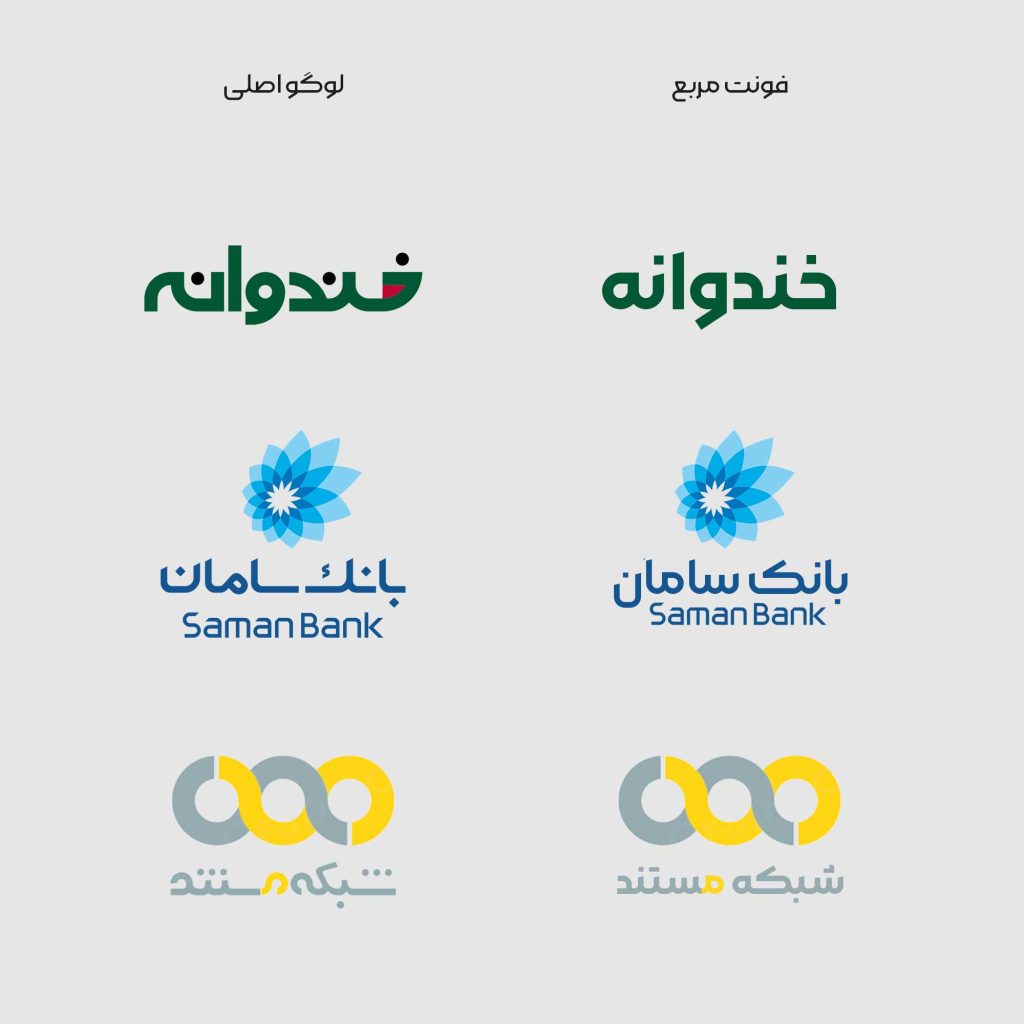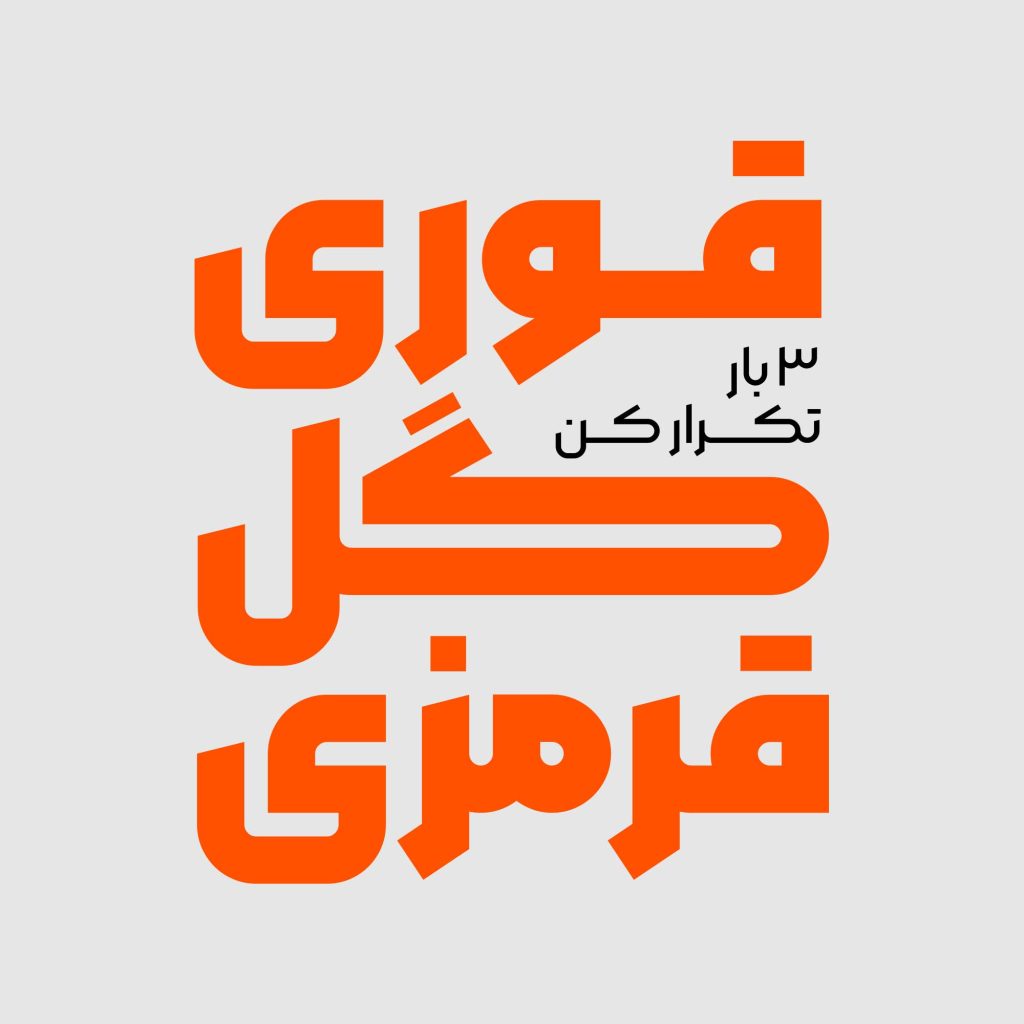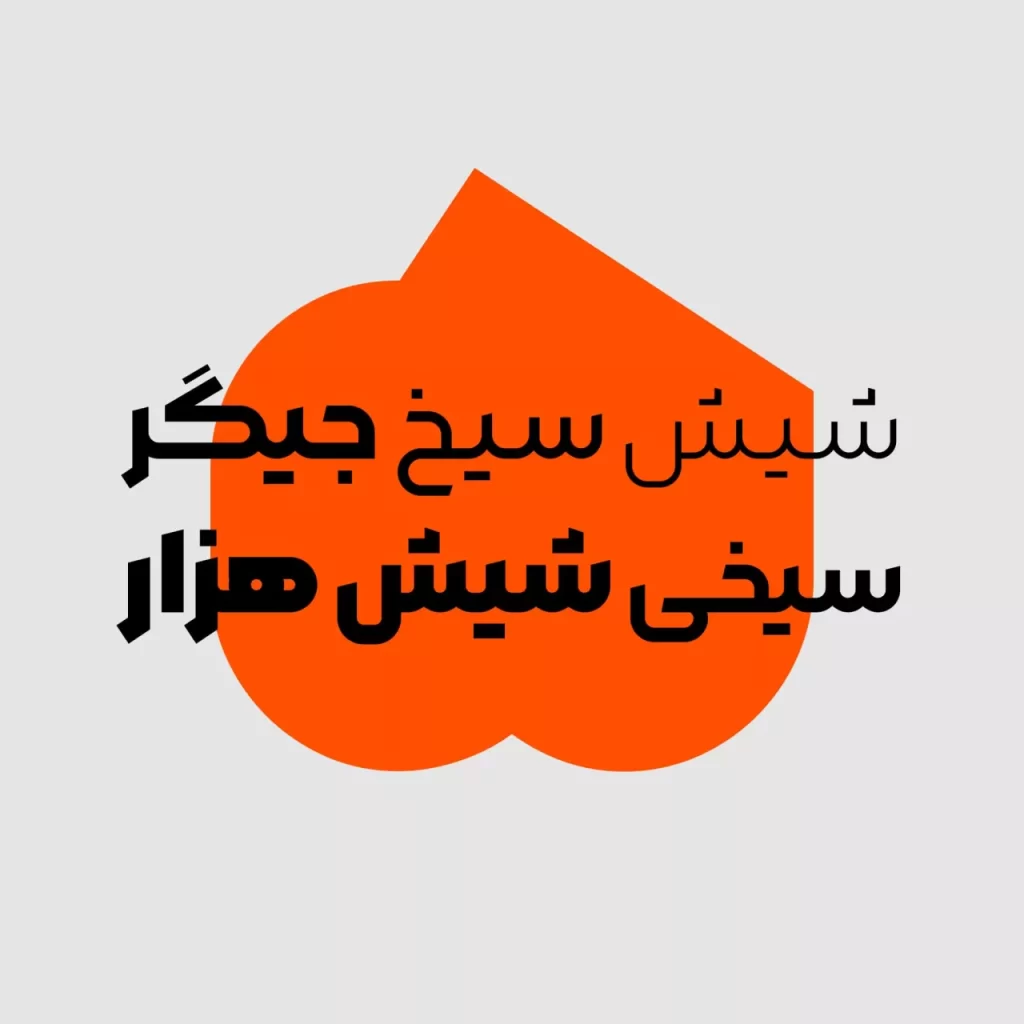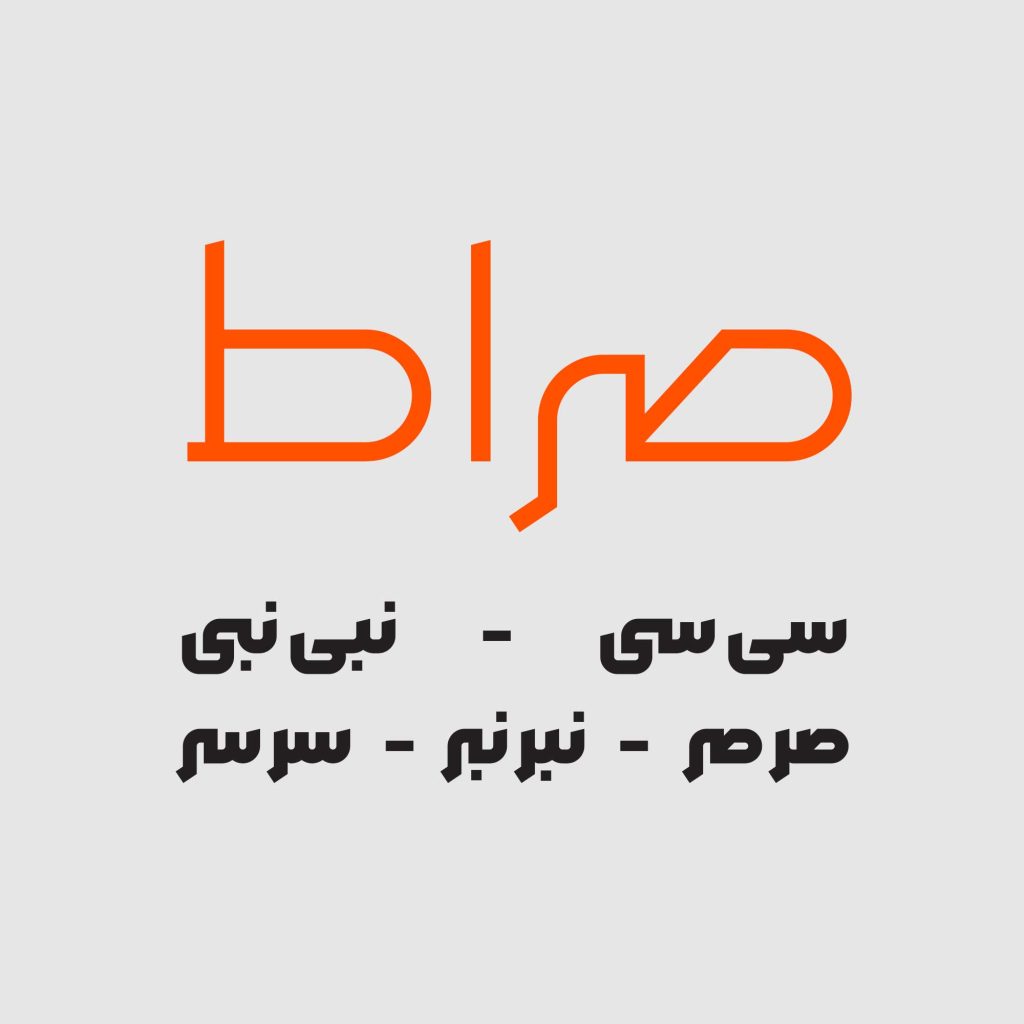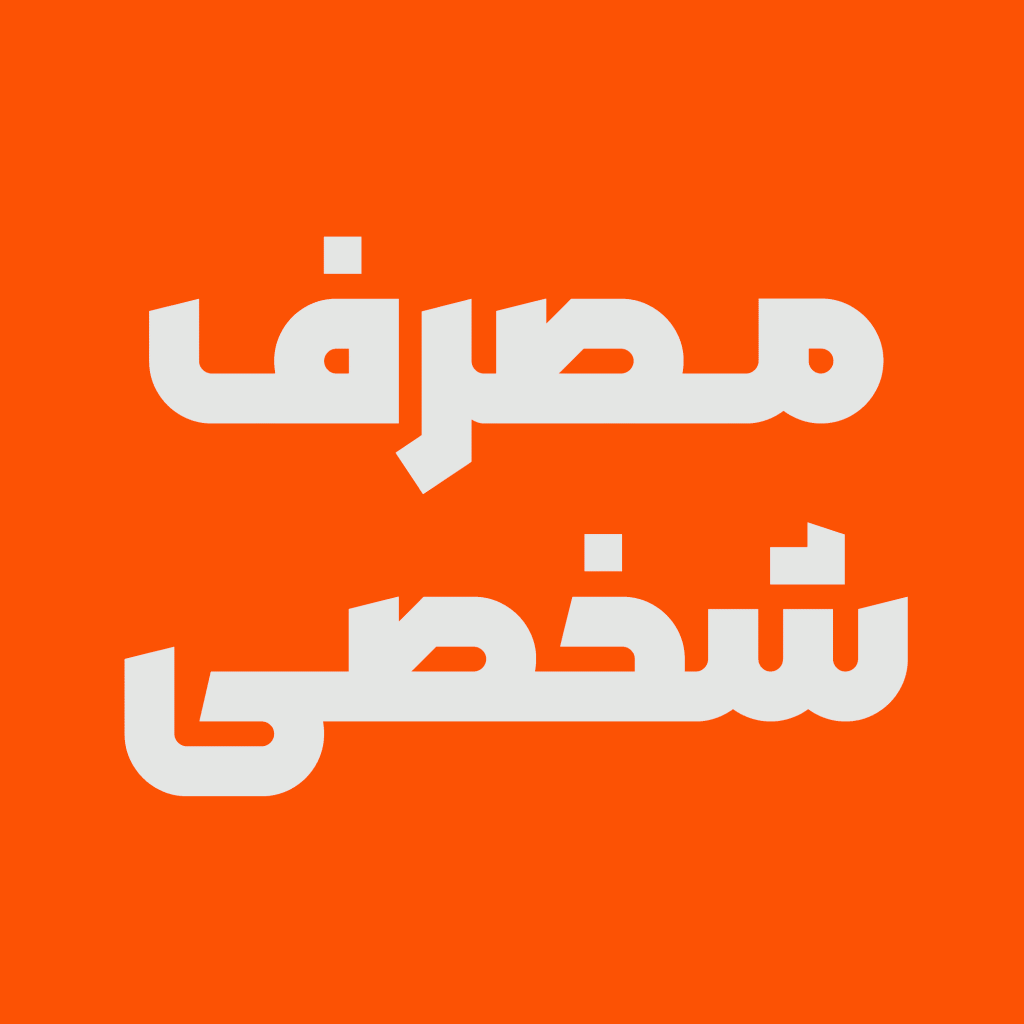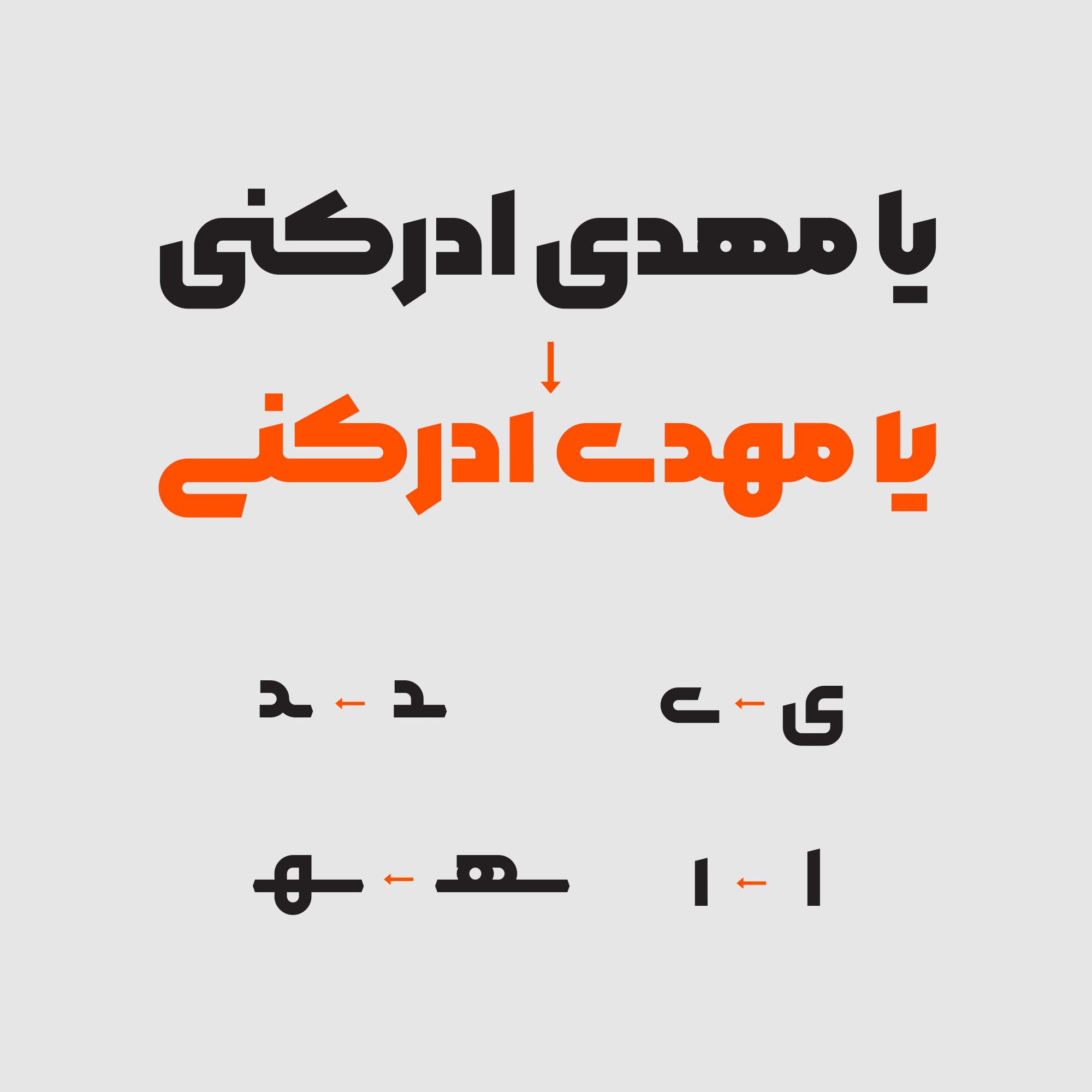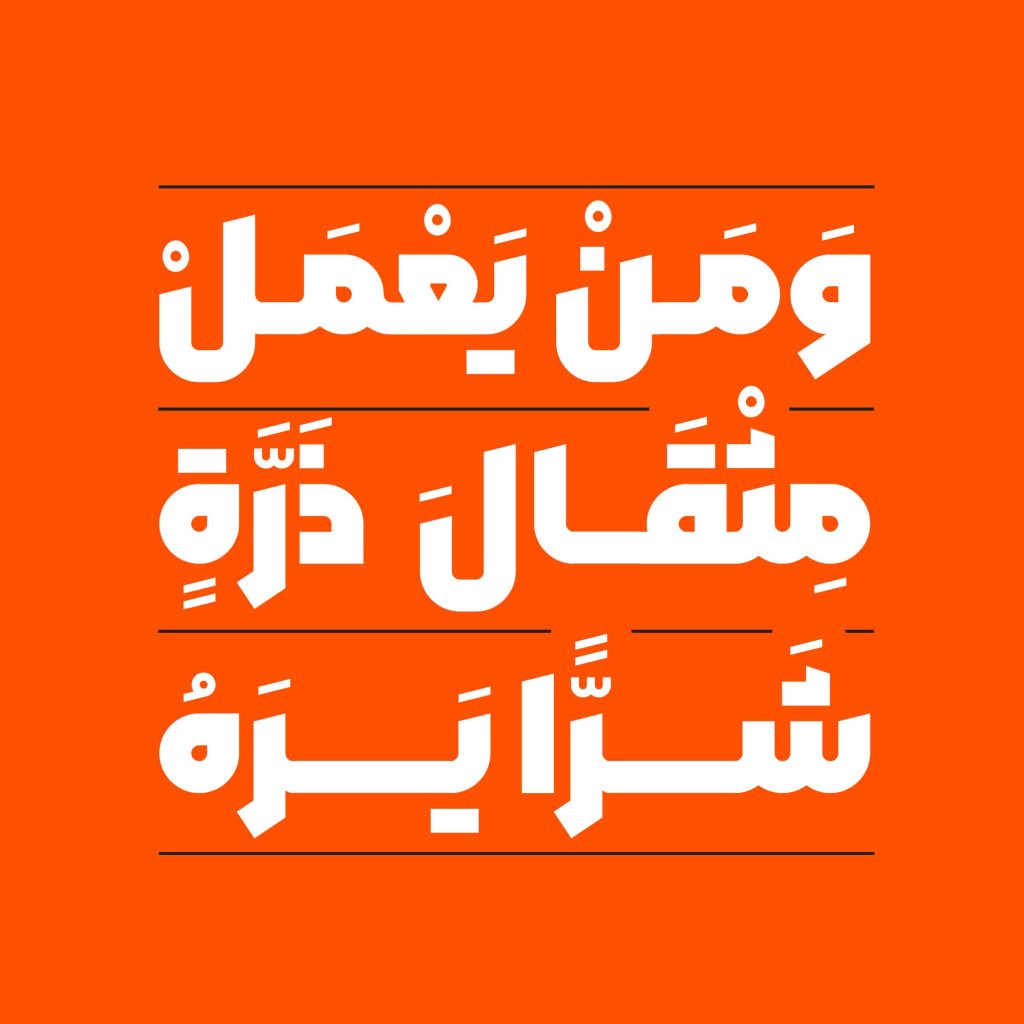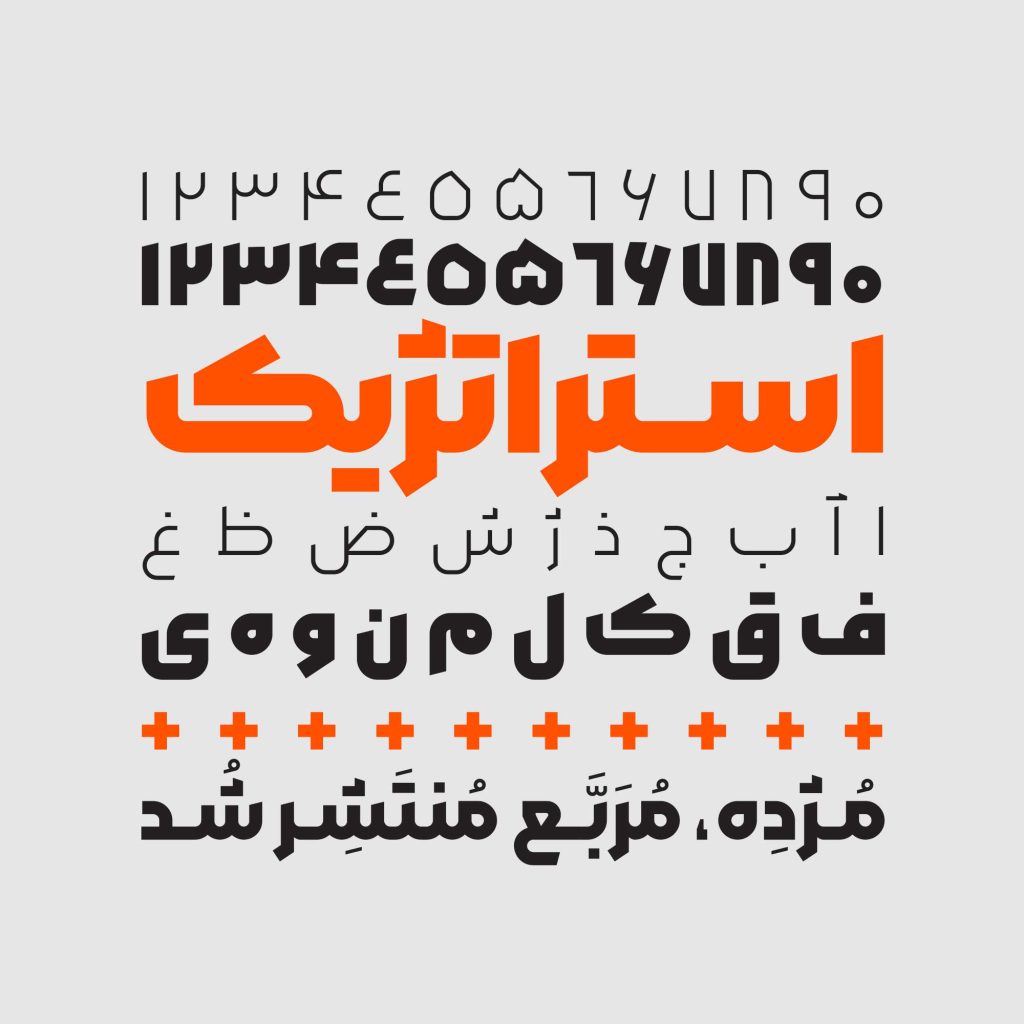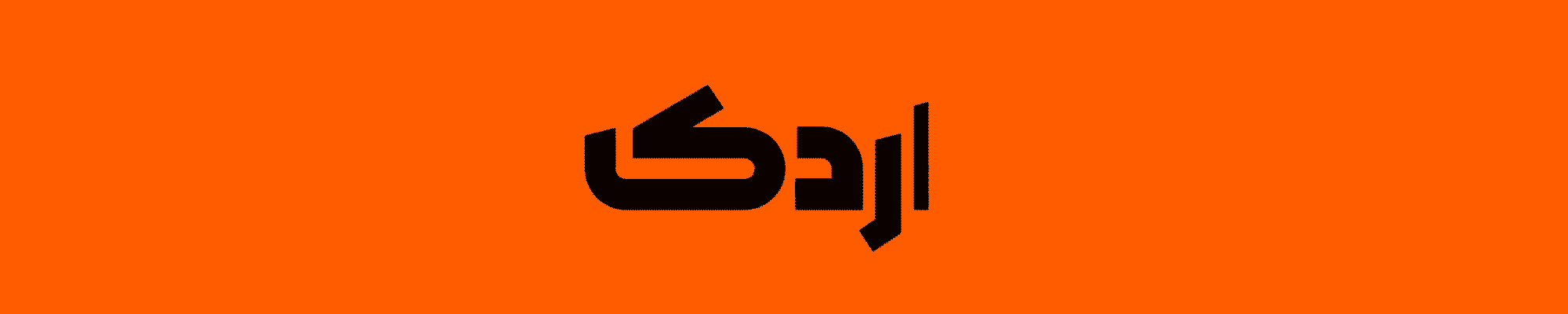
فونت مربع
فونت مربع تایپ فیسی که با دانلود و خرید آن تقریبا اکثر نیاز های خود را مرتفع می سازید. اساس و شاکله این قلم مبتنی بر خانواده کاملا هندسی است . از هم نشینی شبکه ای از دایره ها و مربع ها این قلم جذاب و مدرن تشکیل گردیده است. تایپ فیسی برای کلمات و عبارات کوتاه که جاذبه و گیرایی آن بی شک نگاه خوانندگان را به خود جذب می نماید.
این قلم با روحیه پر انرژی و امروزی که دارد مناسب برای موضوعات تجاری و مدرن و تبلیغاتی است از قبیل طراحی وردمارک، اسلاید و کاورهای تبلیغاتی ، مطبوعات شبکه های اجتماعی و چاپ و بسته بندی و … همانطور که پیش تر نیز خدمت شما عرض کردیم مربع قلمی همه منظوره است.
با دقت در فرم های طراحی گلیف های این تایپ فیس، می توان دریافت که نسبت فضای مثبت به فضای منفی در نظر گرفته شده و کِرو ها دقیقا با محیط دایره همراستا گشته اند.
از نقطه نظر شباهت می توان این قلم زیبا را می توان هم نوع و هم شکل فونت رخ در نظر گرفت. هر دو این تایپ فیس ها از خانواده هندسی می باشند . همانطور که واضح و مشخص می باشد توجه به جزئیات در هر دو این قلم ها امری غیر قابل انکار می باشد.
مربع مناسب پوستر عناوین و ساخت لوگو تایپ
فرم طراحی در این تایپ فیس مناسب برای استفاده و طراحی ورد مارک Wordmark می باشد یعنی می توان از این قلم به عنوان لوگو تایپ نیز با عنایت به هندسی بودن و فرم خاص آن نیز استفاده نمود . پس می توانید به کمک نرم افزار های طراحی از جمله آدوبی ایلسترتور و فتوشاپ یا حتی اینشات لوگو های مورد نظر خود را طراحی و ایجاد نمائید.
مربع دارای خانواده ای از وزن ها است . این تایپ فیس با پشتیبانی از 9 وزن نیاز علاقه مندان و طراحان را کاملا رفع می نمائید . اما نکته مهم تر دارا بودن فایل متغییر یا وریبل فونت در بسته این محصول است. شما در یک فایل تمامی 9 وزن و کشیدگی ها و حالت های مختلف نقطه گذاری یا حتی ترکیبات مختلف و در یک کلام همه چیز را در یک فایل دارید . این سبب حجم کمتر و سرعت بیشتر به خصوص در دنیای وب می شود.
پشتیبانی از حروف جایگزین در تایپ فیس مربع
مربع همچنین با دارا بودن حروف و ترکیبات مختلف خلق تنوع و زیبایی بیشتر را در انتخاب های شما میسر ساخته است . در فایل راهنما می توانید با نحوه استفاده از این لیگچر ها و استایلیتیک ها آشنا شوید. خب دیگه توضیح بیشتر نیاز نیست کافیه تصاویر نمونه نمونه از این تایپ فیس خاص و زیبا رو مشاهده کنین .
فارسی ، انگلیسی ، عربی
9 وزن
وریبل : تایپ فیس های متغیر دارای ۲ محور: تغییر وزن / کشیده
این محصول در سه زبان فارسی، عربی و انگلیسی قابل استفاده است. Roboto به دلیل شباهت فرمی مکمل شده است.
در طراحی نسخهی دوم ، زمان بیشتر و سعی افزون تری سعی شده که ضمن مرتفع نمودن کاستی های نسخهی اول، میزان کارایی و بهره وری آن نیز افزایش یابد. پس ضمن حفظ ساختار کلی و تیپ شخصیتی خاص این تایپ فیس ، شاهد تغییراتی مهم در نسخه جدید می باشیم.